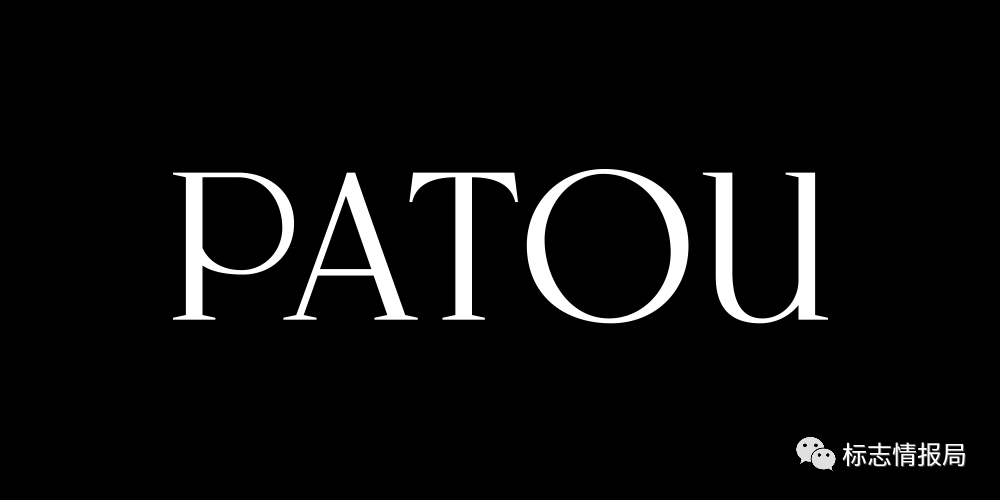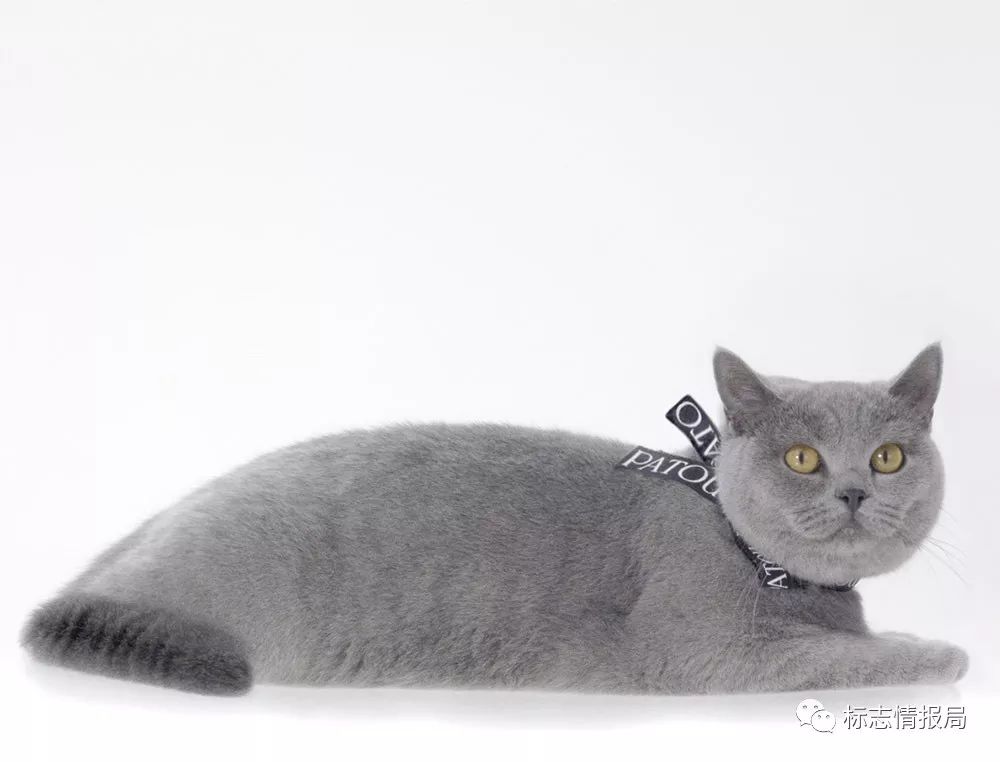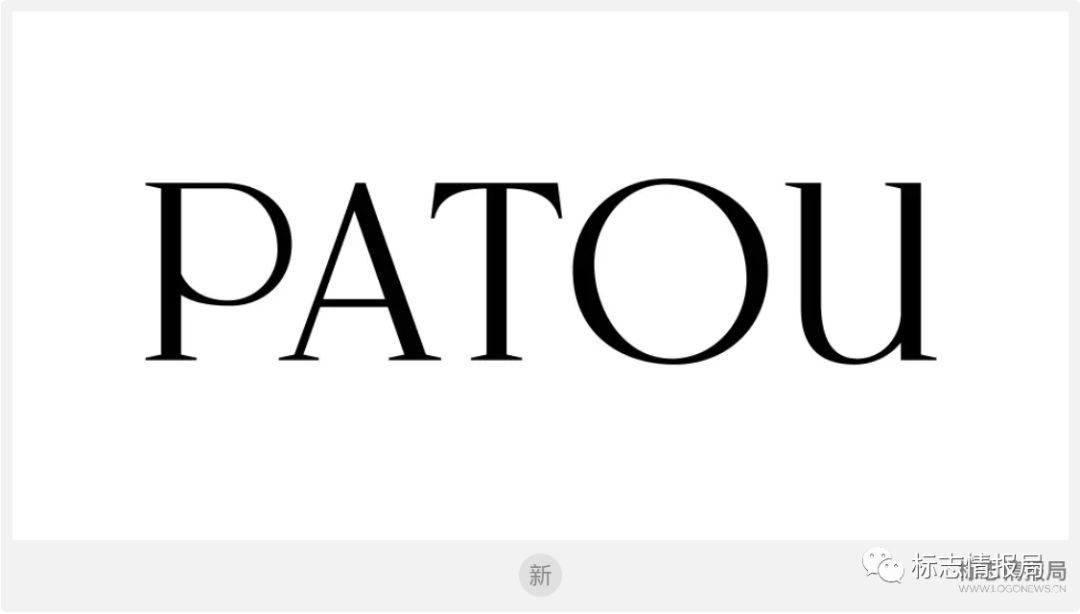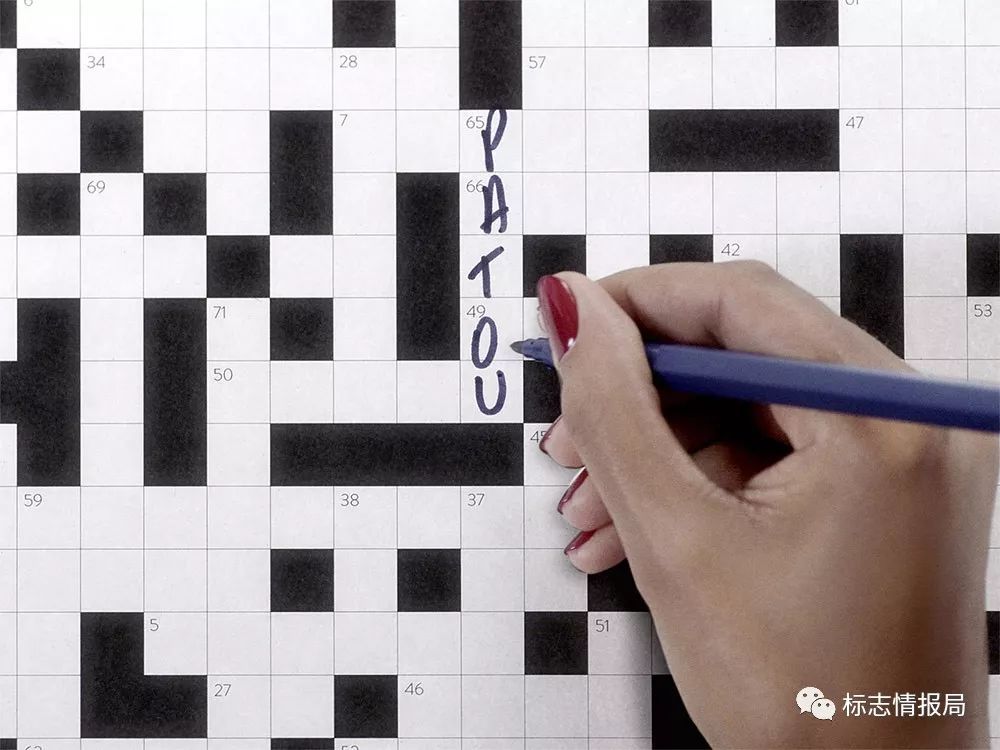
Jean Patou换LOGO,终于不再无衬线!
前不久,全球最大奢侈品集团LVMH宣布与美国艺人蕾哈娜推出全新奢侈品牌Fenty,近日,LVMH又宣布将去年收购的品牌Jean Patou进行全新定位,并发布了全新的品牌名称和品牌LOGO。
著名的奢侈品品牌Jean Patou由创始人Jean Patou(让·巴杜)创立于1914年,Jean Patou是二十世纪20年代到30年代最伟大的服装设计师之一。他以设计毛衣、运动休闲服装而闻名世界。
去年8月份,LVMH集团正式收购Jean Patou,9月份Guillaume Henry出任创意总监,随后在Guillaume Henry的带领下对Jean Patou进行了大规模的调整,将该品牌旗下久负盛名的Joy香水名字给了Dior香水,并邀请美国演员Jennifer Lawrence为最新的Dior Joy香水代言。
最近,Jean Patou公布了全新的品牌名称和品牌LOGO,名字去掉了Jean,只保留了创始设计师姓氏的Patou。
其实这种改名已有很多先例可参,比如香奈儿从Coco Chanel改为Chanel,克里斯汀·迪奥从Christian Dior更改为Dior。
此外,Patou全新的LOGO以外的没有使用当下奢侈品牌钟爱的无衬线字体,让品牌保留了文化和年代感。
随着新形象的发布,Patou还公布了一系列宣传短片,短片中有带着Patou 新LOGO缎带的猫咪,也有化身为甜品店蛋糕纸的品牌LOGO在一堆配色鲜艳的蛋糕中亮相。
据悉,Patou已经告别高级时装界超过20年,在这之前,它的名声与Chanel相当的存在。
所以导致很多消费者,特别是年轻一代,都将Patou当作一个单纯的香水品牌。
此次在Guillaume Henry的带领下进行全面的品牌重塑,并于2019年9月在巴黎时装周发布全新的高级时装系列,正式回归高级时装界。